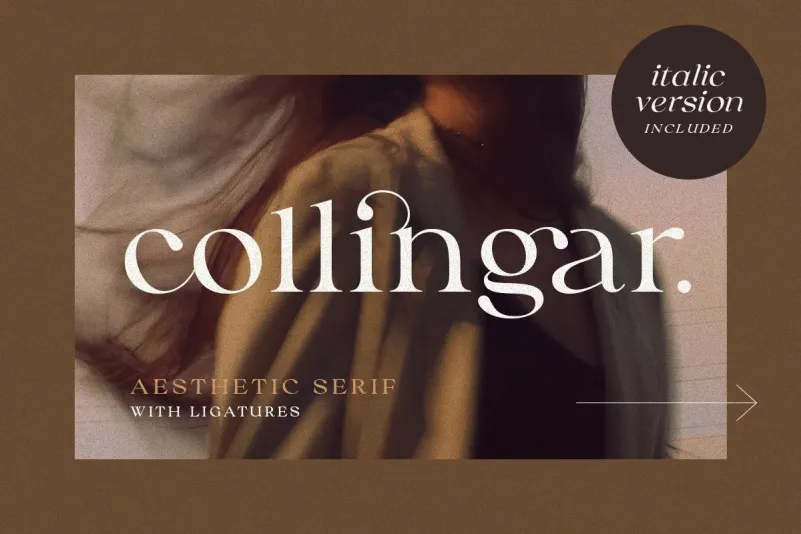
A Collingar Font é uma elegante serif que combina clareza e detalhe para criar texturas sofisticadas. Sua ligatura única permite que você use essa fonte tanto no estilo de produto quanto na exibição, oferecendo um tom mais formal a seus projetos gráficos. Além disso, inclui uma versão em itálico, permitindo-lhe explorar diferentes estilos e harmonizar perfeitamente com coleções de grafismos script. Esta fonte é ideal para diversificadas aplicações, como invitations casuais ou até mesmo a criação de marcas inovadoras. Com suporte múltiplo idioma e codificado PUA, a Collingar Font está pronta para atender aos mais variados requisitos criativos. Ela traz a sofisticação e as nuances do estilo serif, com um toque moderno que certamente irá se destacar em seu próximo projeto visual.